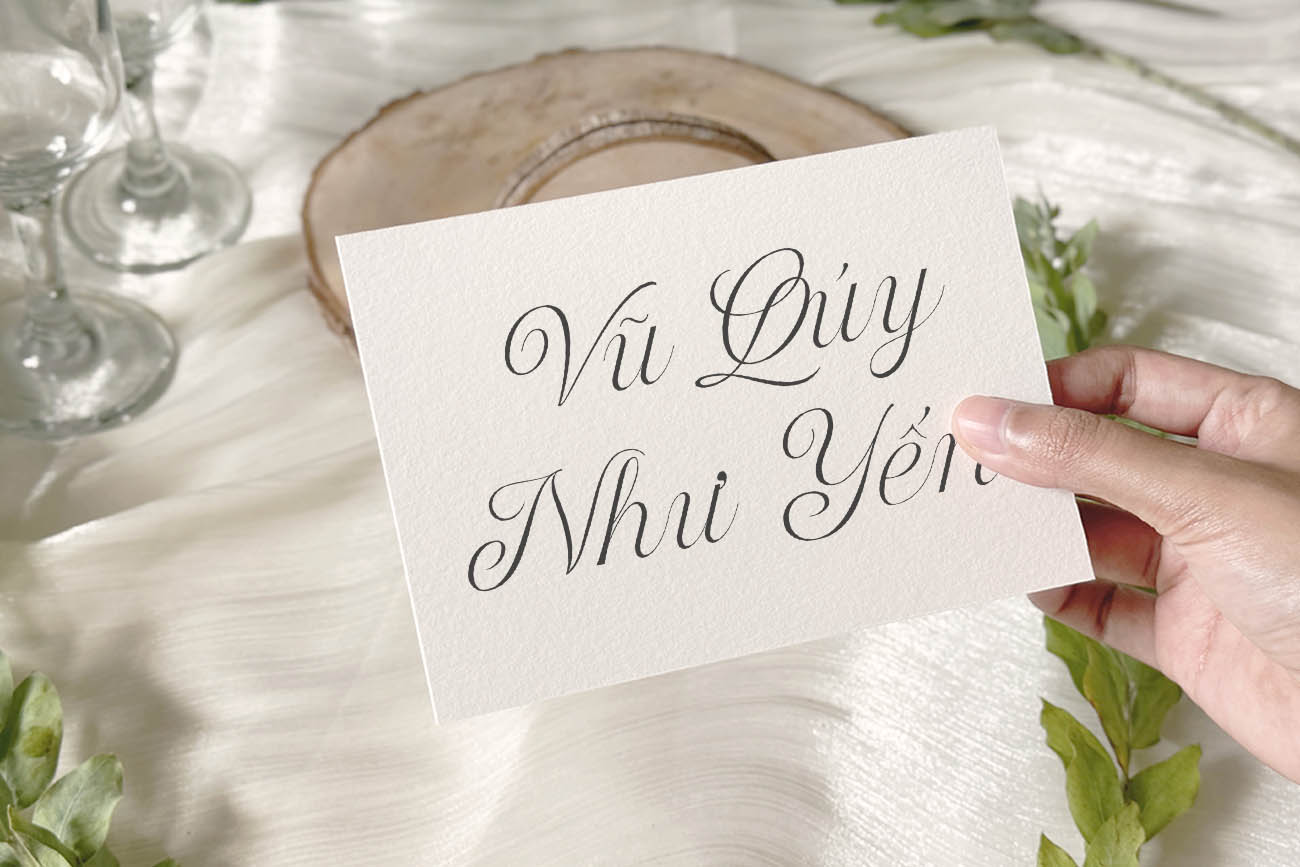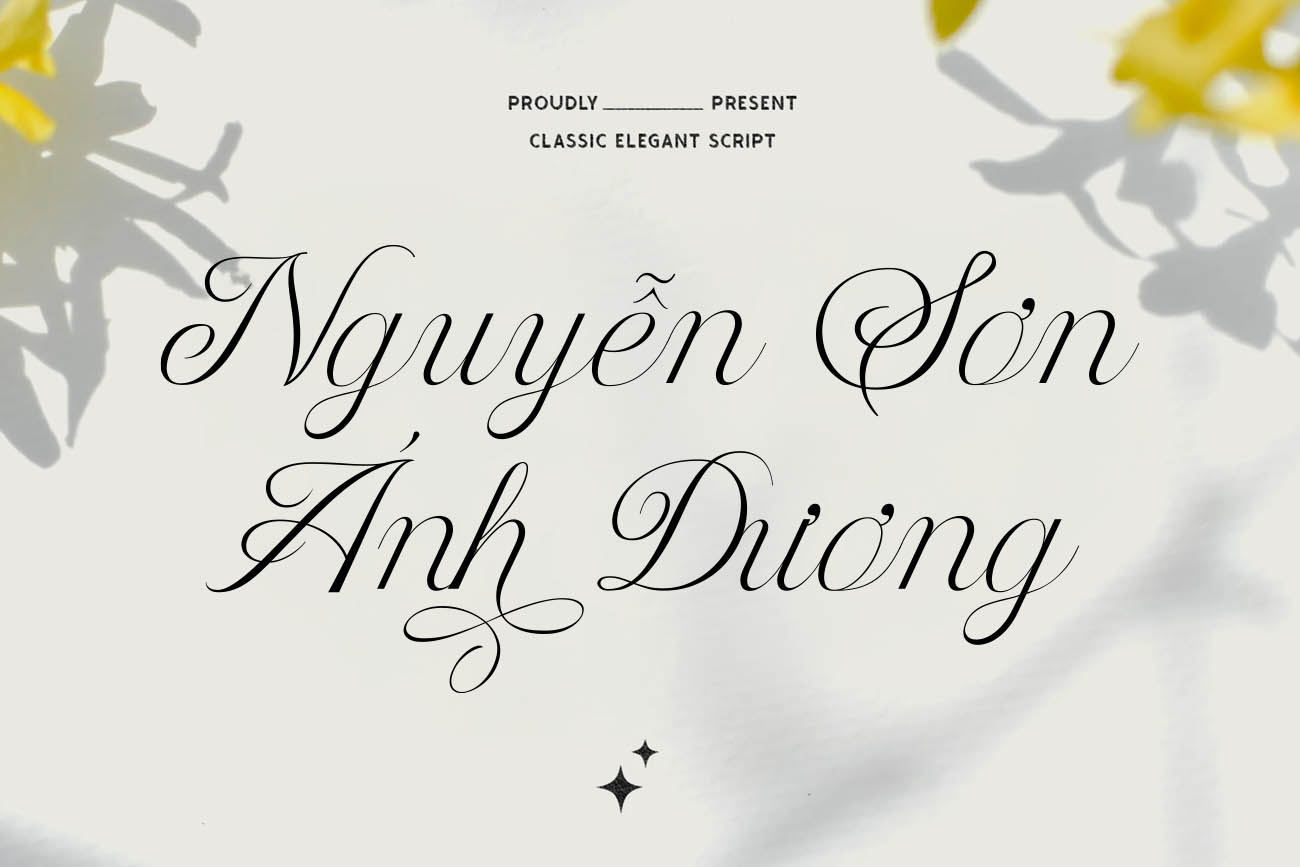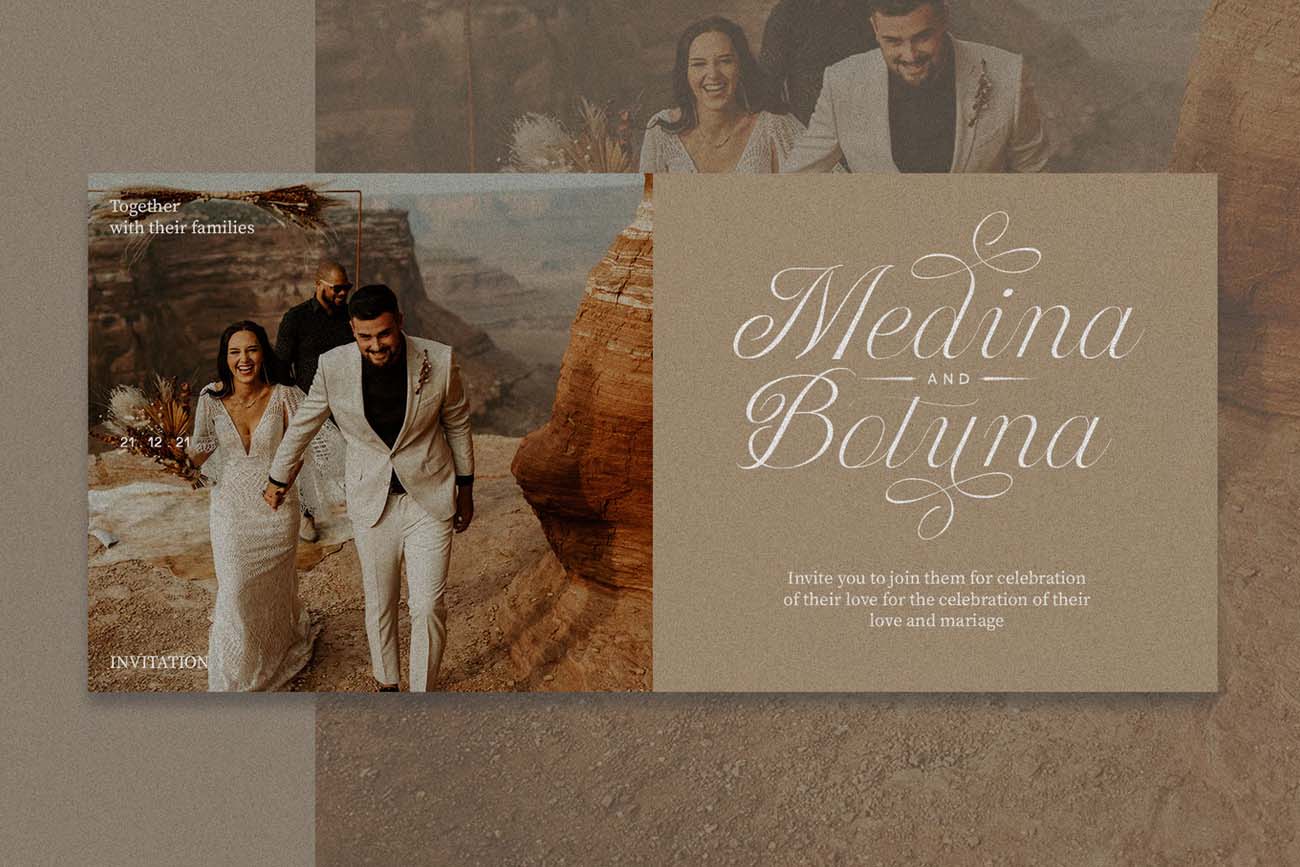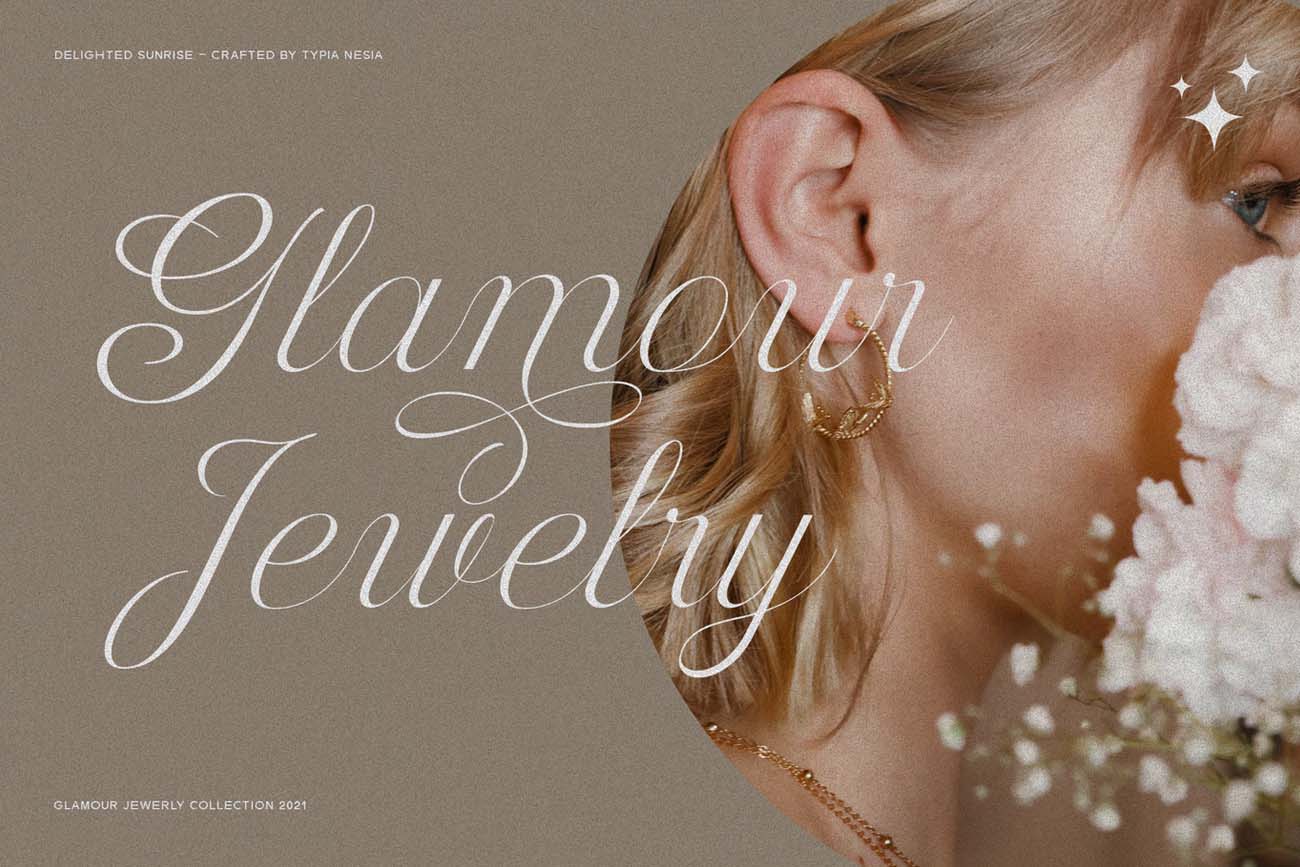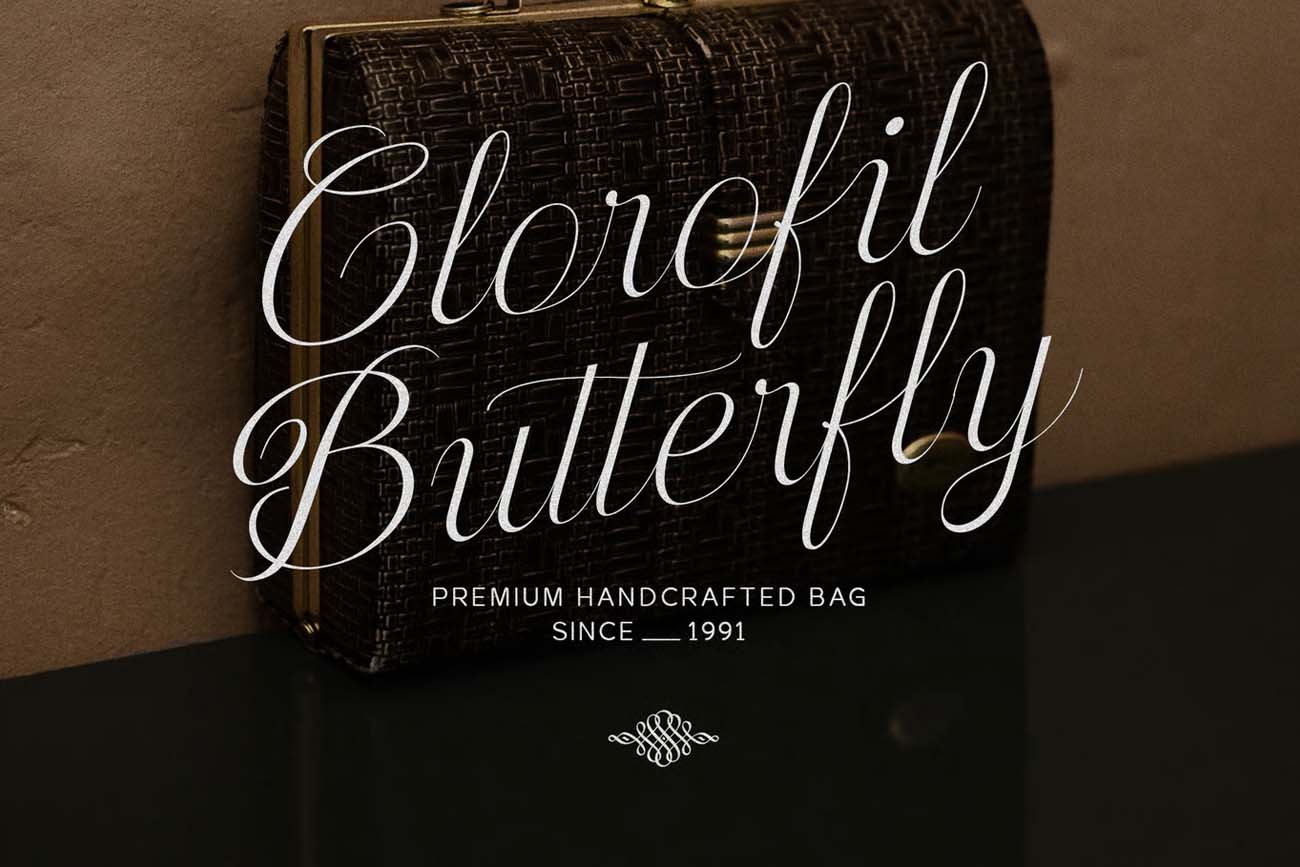
Font Chữ Việt Hóa Lãng Mạn Cho Thiết Kế Thiệp Cưới
Bạn đang tìm kiếm một điểm nhấn tinh tế để thổi hồn vào các dự án thiết kế sang trọng? Delighted Sunrise, một tác phẩm nghệ thuật typography đầy cảm hứng đến từ nhà thiết kế Yipianesia, chính là mảnh ghép hoàn hảo mà bạn đang tìm kiếm. Đặc biệt hơn, để đáp ứng nhu cầu khắt khe của cộng đồng designer Việt Nam, phiên bản TH Delighted Sunrise đã chính thức được ra mắt.
Vẻ đẹp thanh lịch của nghệ thuật Calligraphy
Giữ trọn vẹn tinh thần của bản gốc, TH Delighted Sunrise nổi bật như một font chữ nét mảnh mang đậm chất lãng mạn và sự bay bổng. Từng đường nét uốn lượn, nét thanh nét đậm được tác giả Yipianesia chăm chút vô cùng tỉ mỉ, tạo ra một nhịp điệu thị giác mượt mà trên từng con chữ.
Chính vì sự mềm mại và sang trọng này, đây được giới chuyên môn đánh giá là một font chữ cưới tiêu chuẩn, cực kỳ phù hợp cho những dự án đòi hỏi tính thẩm mỹ cao. Nếu bạn đang trăn trở trong việc lựa chọn một font chữ thiệp cưới ấn tượng để vinh danh tên cô dâu chú rể, hay thiết kế các ấn phẩm sự kiện, logo thương hiệu thời trang, thì TH Delighted Sunrise chắc chắn sẽ làm hài lòng cả những khách hàng khó tính nhất.
Dấu ấn Việt hóa chỉn chu từ TH Team
Mặc dù bản gốc Delighted Sunrise vô cùng xuất sắc, nhưng rào cản khi gõ tiếng Việt có dấu luôn làm gián đoạn mạch sáng tạo của các designer. Thấu hiểu khó khăn đó, đơn vị TH Team đã dành trọn tâm huyết để xử lý và cho ra đời phiên bản font chữ Việt hóa hoàn chỉnh mang tên TH Delighted Sunrise.
Trong quá trình thực hiện, TH Team không chỉ đơn thuần là gắn thêm các dấu câu. Đội ngũ đã nghiên cứu kỹ lưỡng để bộ dấu tiếng Việt hòa quyện một cách tự nhiên nhất vào những nét móc, nét hất đặc trưng của phông chữ script. Khoảng cách giữa các ký tự (kerning) cũng được tinh chỉnh tối ưu, đảm bảo đoạn văn bản khi hiển thị luôn đồng đều, sắc nét nhưng không hề đánh mất đi sự tự do, lãng mạn nguyên bản.
Lời kết
Sự kết hợp giữa tài năng thiết kế nguyên bản của Yipianesia và sự tỉ mỉ, am hiểu ngôn ngữ của TH Team đã mang đến cho cộng đồng sáng tạo một công cụ typography tuyệt vời. Hãy bổ sung ngay TH Delighted Sunrise vào thư viện của bạn để sẵn sàng kiến tạo nên những tác phẩm thiết kế đầy cảm xúc, chuyên nghiệp và chạm đến trái tim người xem.